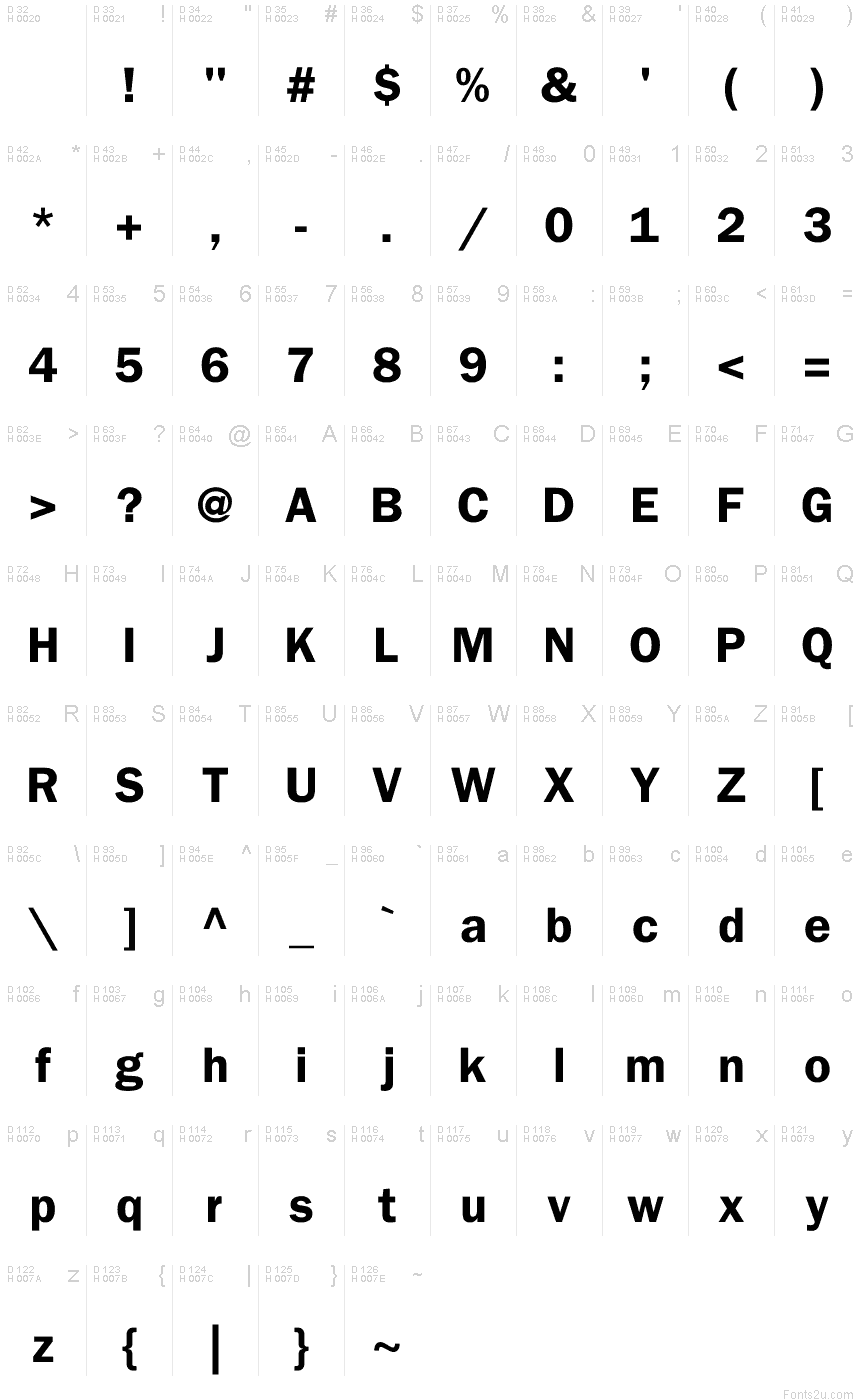
Un Graphic Bold, di Koaunghi Un, è un font sans serif bold gratuito con un carattere schietto, che ricorda l'estetica digitale delle origini. Le lettere sono compatte e incisive, un mix di curve arrotondate e tagli squadrati con giunzioni strette che conferiscono al font un ritmo solido e concreto.
È ideale per branding, poster, copertine di riviste, titoli e intestazioni di interfacce dove serve una voce sobria ma con peso e presenza. Essendo un font gratuito, funziona bene anche per nomi brevi su packaging o banner web, poiché le forme pesanti catturano l'attenzione senza bisogno di fronzoli.